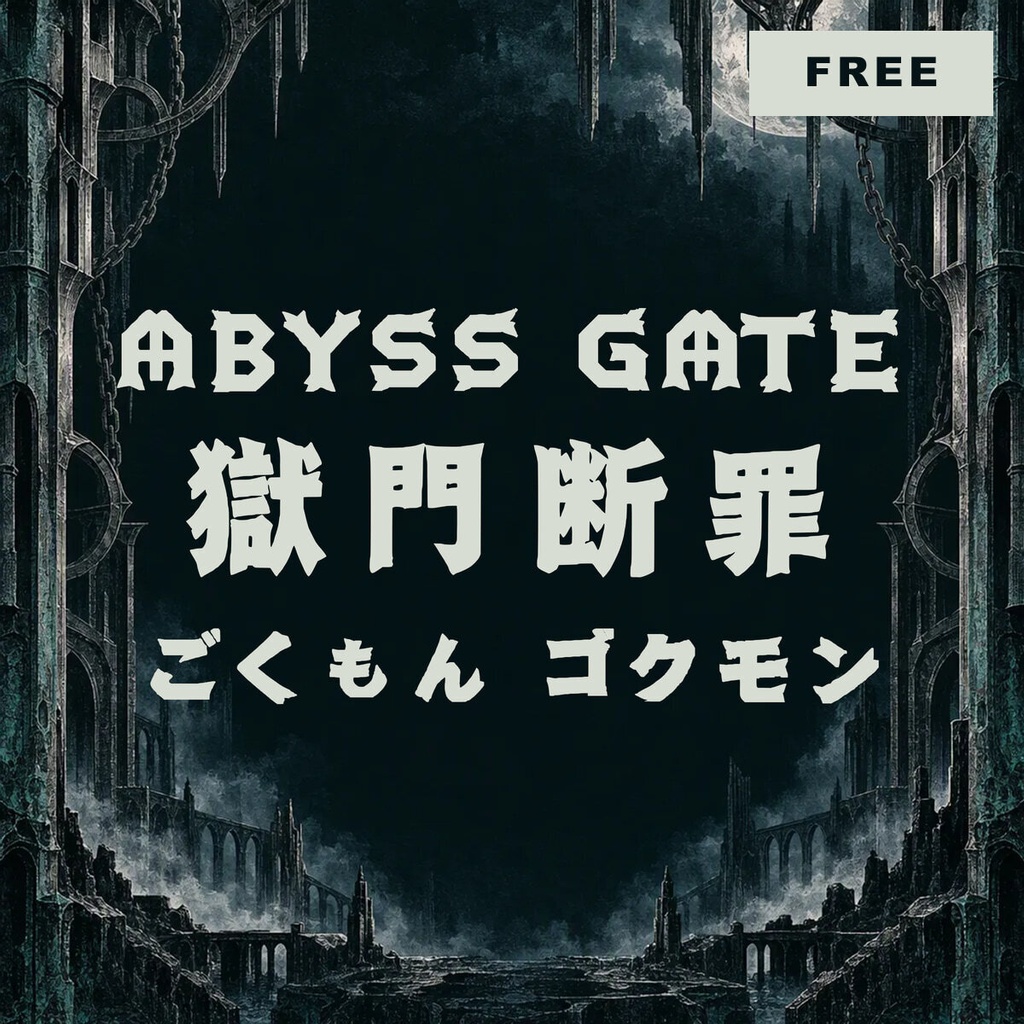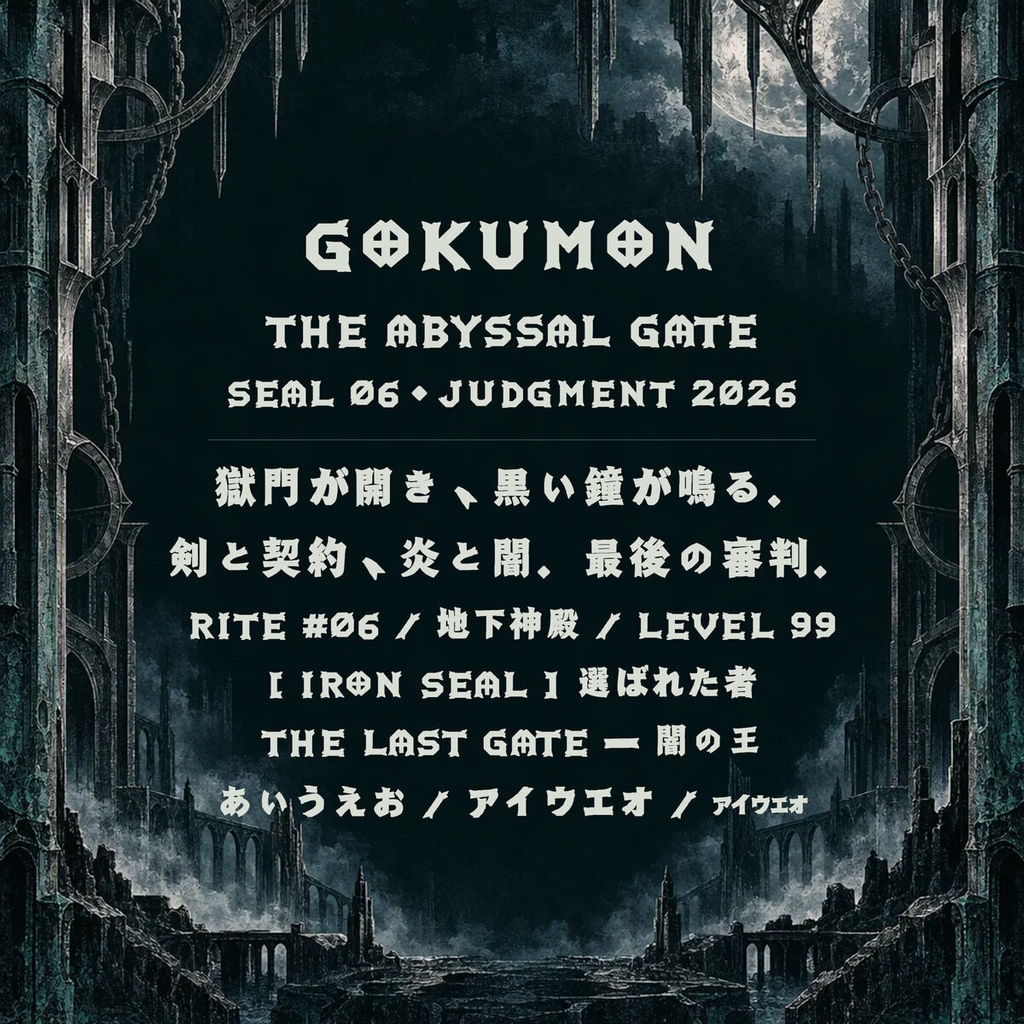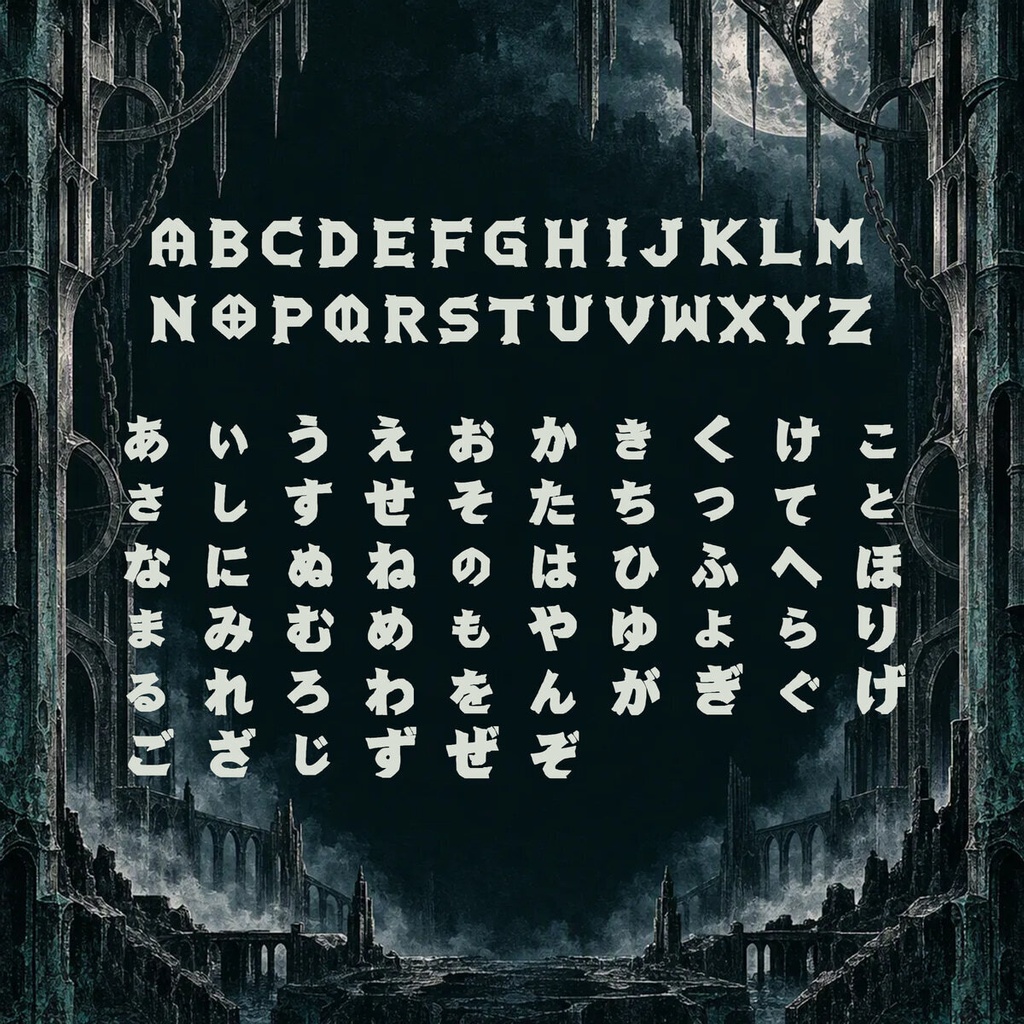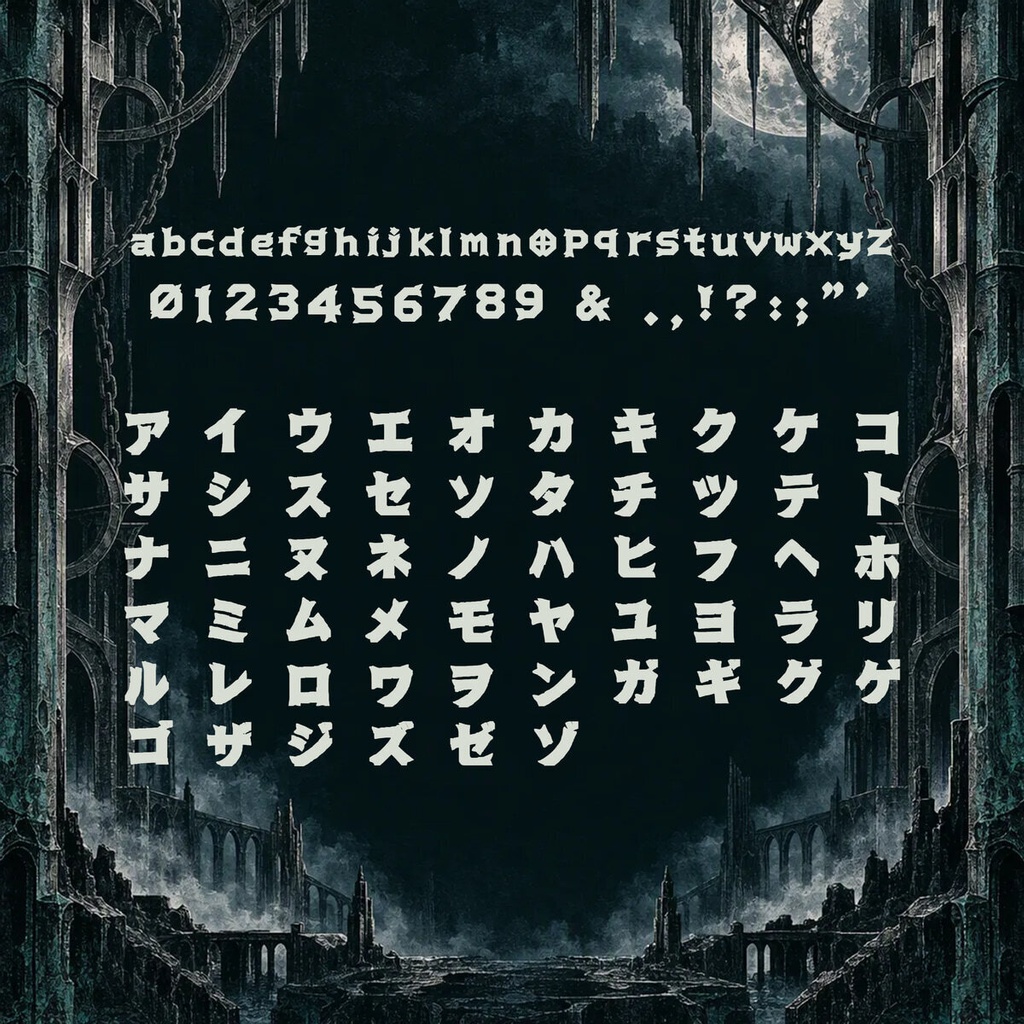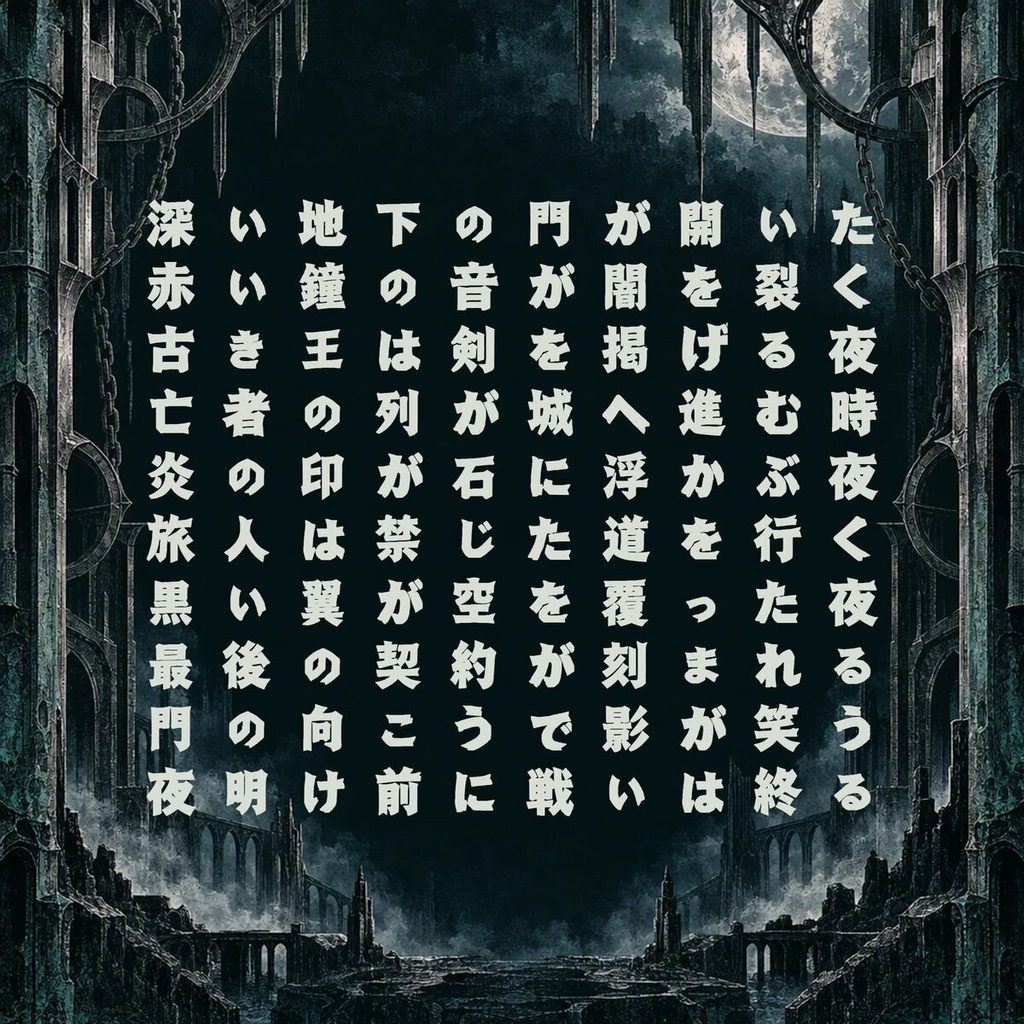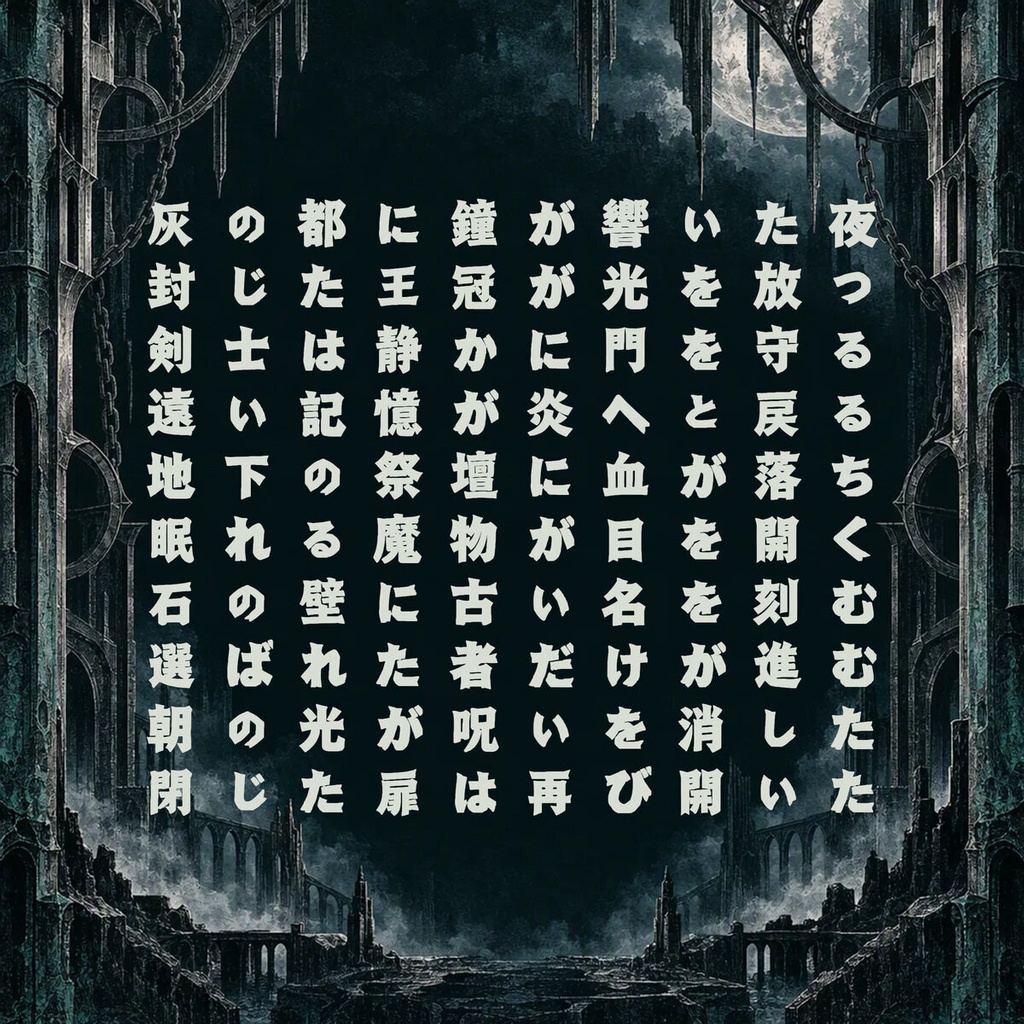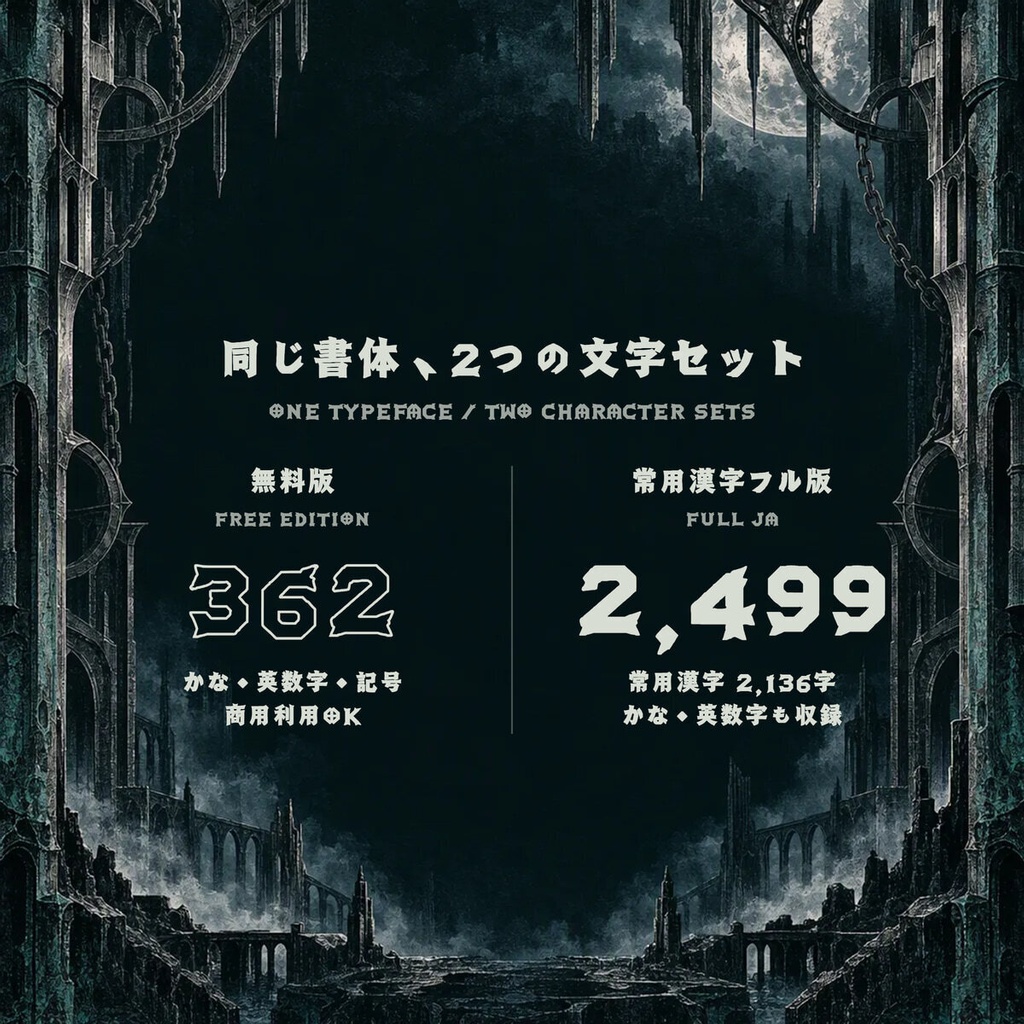
十字封印と二股の刃先を備えた、冥界の門を思わせる重厚なディスプレイ書体です。 A monumental dark-fantasy display face forged with cross-seal counters and forked ironfang terminals. 십자 봉인 카운터와 갈라진 칼날 끝으로 벼려 낸 묵직한 다크 판타지 디스플레이 서체입니다. 【用途 / Use / 용도】RPG / ホラーゲーム / TRPG / タイトルロゴ / メタル・ダークウェーブ For RPGs, horror games, TRPGs, title logos, metal, and darkwave artwork. RPG / 호러 게임 / TRPG / 타이틀 로고 / 메탈·다크웨이브 아트워크 ━━━━━━━━━━━━━━━━━━━━━━━━━━━ 【無料版 / Free Edition / 무료판】 ━━━━━━━━━━━━━━━━━━━━━━━━━━━ ラテン文字・ひらがな・カタカナ・記号を収録した、商用利用可能な無料フォントです。 漢字は収録していません。ロゴ、タイトル、動画、配信、同人作品などでお使いいただけます。 This is a free, commercial-use font covering Latin, hiragana, katakana, and symbols. Kanji are not included. Use it for logos, titles, video, streaming, and indie works. 無料版 / Free edition: 362文字 — ¥0 ラテン大文字26 / ラテン小文字26 / 数字10 / ひらがな81 / カタカナ91 / 半角カナ・句読点61 / 記号・句読点66 / スペース1 ━━━━━━━━━━━━━━━━━━━━━━━━━━━ 【常用漢字フル版 / Full JA Upgrade】 ━━━━━━━━━━━━━━━━━━━━━━━━━━━ 無料版の全文字と常用漢字2,136字を収録した全2,499文字版は ¥3,200 です。 Full JA includes every free-edition character plus all 2,136 Joyo kanji (2,499 characters total). ▶ 常用漢字フル版 / Full JA: https://mojiworks.booth.pm/items/8840459 ━━━━━━━━━━━━━━━━━━━━━━━━━━━ 【フォント仕様 / Specification】 ━━━━━━━━━━━━━━━━━━━━━━━━━━━ 形式 / Format : OpenType TrueType (.ttf) / Web (.woff2) 文字コード / Encoding : Unicode 動作環境 / Platform : Windows / macOS / Web browsers 収録字一覧 / Charset : 各ZIP内の CHARSET.txt 同梱ファイル / Bundled files: .ttf — デスクトップ用 / desktop .woff2 — Web 用 / web README.txt / README.jp.txt LICENSE.txt / LICENSE.jp.txt CHARSET.txt — 収録字一覧 / character list portfolio.pdf — モジワークス全書体ポートフォリオ (EN) portfolio.jp.pdf — モジワークス全書体ポートフォリオ (JP) 商品プレビュー画像 / product preview images ━━━━━━━━━━━━━━━━━━━━━━━━━━━ 【利用規約 / License Summary】 ━━━━━━━━━━━━━━━━━━━━━━━━━━━ ご購入・ダウンロードにより本規約に同意したものとみなします。著作権は Mojiworks に帰属します。 By downloading or purchasing this font you agree to these terms. © Mojiworks. The bundled LICENSE.txt / LICENSE.jp.txt is authoritative; this is a summary. ●使用条件 / Permitted use - 1ライセンス = 購入者本人。個人・商用利用OK。 One license is granted to a single user (the purchaser). Personal and commercial use is permitted. - 静的・ラスタライズ済み成果物(印刷物 / 動画 / グッズ / ロゴ / タイトル / ラスタライズUI)は常に許可。 Static, pre-rendered output (print, video, merchandise, logos, titles, rasterized UI text) is always permitted. - 同梱 .woff2 を購入者本人のサイトで CSS @font-face によりWebフォントとして使用可。 The bundled .woff2 may be served via CSS @font-face on a website owned or operated by the purchaser. ●条件付き利用 / Conditional use — game / app / software embedding - ゲーム・アプリ・ソフトへの組み込みは、エンドユーザーが生の .ttf / .woff2 を抽出できない形式に限り許可。 例: SDF / MSDF フォントアトラス、ビルド時ビットマップ化、暗号化・独自フォーマットへのパッキング、難読化コンテナ等。 Embedding in games, apps, or software is permitted only if the raw .ttf / .woff2 cannot be extracted by end users (e.g. SDF/MSDF font atlases, build-time bitmap atlases, encrypted or custom asset packing, obfuscated containers). - 生の .ttf / .woff2 をビルドにそのまま同梱する用途は標準ライセンス対象外です。別途「ランタイム組み込みライセンス」をご相談ください。 Shipping the raw .ttf / .woff2 inside a build is NOT covered by the standard license — please contact us for a separate runtime-embedding license. ●利用規模 / Scale limit - 標準ライセンスは 1製品 / 1サイト あたり 年間およそ 100,000 インストール/ダウンロード/ユニークビジターまでをカバーします。 The standard license covers usage up to approximately 100,000 installs, downloads, or unique visitors per year, per product or site. - これを超える規模、または従業員 50 名超の組織(タイトルのパブリッシャー含む)でのご利用は「拡張ライセンス」をご相談ください。 Beyond this scale, or for organizations with more than 50 employees (including the publisher of the title using the font), please contact us for an extended license. ●禁止事項 / Prohibited - フォントファイル本体の再配布・譲渡・販売・貸与・サブライセンス。 Redistribution, resale, lending, or sub-licensing of the font file itself. - 生 .ttf / .otf の公開Webサーバー / CDN / ファイル共有サービスへのアップロード。 Uploading the raw .ttf / .otf to public web servers, CDNs, or file-sharing services. - 他者運営サイトからの .woff2 のホットリンク。 Hot-linking the supplied .woff2 from a site not owned by the purchaser. - フォーマット変換(独自Webフォント化を含む)、グリフデータの抽出、派生・類似フォントの制作・配布。 Format conversion (including building your own webfont), glyph extraction, or creating / distributing derivative or look-alike fonts. - 生成AIの学習、または画像・テキスト生成のスタイル参照としての使用。 Use for training generative-AI models or as a style reference for AI generation. - 本フォント自体の主たる商標としての登録(フォントで作った制作物の商標化は可)。 Trademark registration of the font itself as a primary mark (trademark of works made with the font is allowed). - 公序良俗に反する用途(誹謗中傷・犯罪助長・差別等)。 Use violating public order or morals (defamation, incitement to crime, discrimination, etc.). 詳細は同梱の LICENSE.txt / LICENSE.jp.txt をご確認ください。 For the full license, see the bundled LICENSE.txt / LICENSE.jp.txt. ━━━━━━━━━━━━━━━━━━━━━━━━━━━ 【カスタムフォント制作 / Custom Font Service】 ━━━━━━━━━━━━━━━━━━━━━━━━━━━ あなたのプロジェクトの世界観・雰囲気に合わせた、完全オーダーメイドのフォント制作を承ります。 ゲーム / アニメ / ブランド / VTuber / 同人作品のロゴ・タイトル用書体、独自スタイルのディスプレイ書体、収録字の拡張など、お気軽にご相談ください。 We craft fully custom fonts tailored to your project's visual identity and requirements. Please contact us for original display faces, logo/title fonts, expanded character coverage, extended licenses, or runtime-embedding licenses. ▶ Mojiworks ショップ / Shop: https://mojiworks.booth.pm/